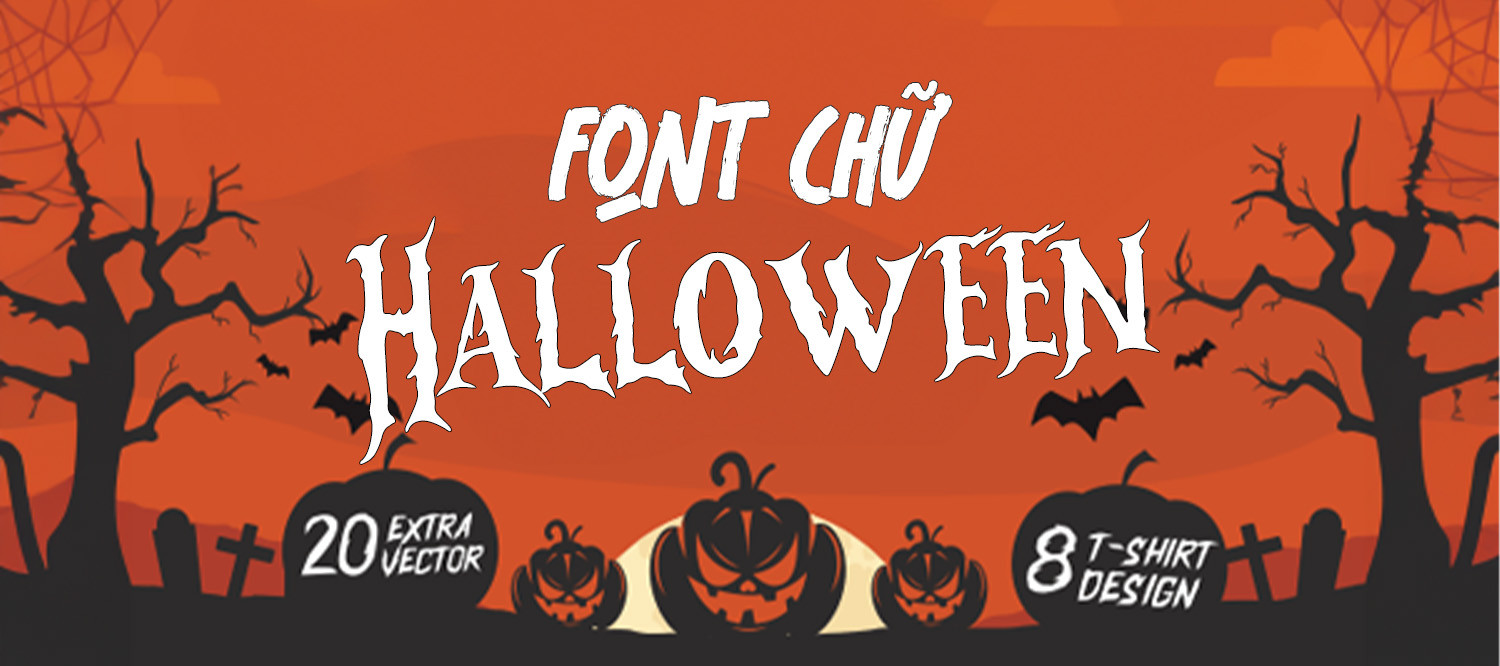
Halloween, ngày lễ kỳ bí và ma quái, luôn mang đến cho chúng ta cảm giác hồi hộp và thú vị. Để tạo ra những nội dung hấp dẫn và phù hợp với chủ đề này, việc sử dụng font chữ Halloween đóng vai trò vô cùng quan trọng. Những font chữ đặc biệt này không chỉ giúp thể hiện được không khí ma mị của Halloween mà còn là yếu tố quyết định trong việc thu hút sự chú ý và tăng cường tương tác của độc giả. Hãy cùng khám phá thêm về các loại font chữ Halloween và cách tận dụng chúng trong nội dung sáng tạo của bạn.
Font chữ Halloween là những loại font được thiết kế đặc biệt để phù hợp với chủ đề Halloween. Chúng thường có các đặc điểm nổi bật như hình ảnh ma quái, thiên về màu sắc tối và các yếu tố đồ họa đặc trưng như những con rắn, quái vật, hay chữ viết phát ra lửa. Việc sử dụng font chữ Halloween mang lại nhiều lợi ích đáng kể cho các chiến dịch truyền thông và nội dung liên quan đến Halloween.
Đầu tiên, chúng giúp tạo ra một không gian thú vị và kịch tính hơn cho người xem, từ đó thu hút sự chú ý một cách nhanh chóng.
Thứ hai, font chữ Halloween giúp tạo ra một phong cách nhất định cho thương hiệu hoặc sản phẩm của bạn trong mùa Halloween, từ đó gia tăng khả năng nhận diện thương hiệu.
Cuối cùng, những font chữ này thường đi kèm với tính tương tác cao, khiến cho người dùng dễ dàng chia sẻ và lan truyền thông điệp của bạn.
Dưới đây là top 8 font chữ Halloween được sử dụng phổ biến hiện nay. Mỗi loại font chữ này đều có tính chất và cảm giác riêng, phù hợp cho các dự án liên quan đến Halloween.
Font chữ brush SVN-Okami là một kiểu chữ chảy độc đáo, mang lại cảm giác thu hút và tự nhiên. Kiểu chữ này đặc biệt thích hợp cho những thiết kế trên nền màu nóng như đỏ và đen, tạo ra sự nổi bật và ấn tượng mạnh mẽ. Với đường nét uốn lượn và cảm giác phóng khoáng, SVN-Okami là sự lựa chọn hoàn hảo cho những thiết kế mang phong cách bí ẩn, ma quái, và kinh dị. Sự kết hợp giữa kiểu chữ chảy và nền màu nóng sẽ mang lại hiệu ứng thị giác mạnh mẽ, tạo nên một không gian đầy lôi cuốn và mê hoặc, thích hợp cho các sự kiện như Halloween hoặc những chủ đề liên quan đến thế giới huyền bí.
Font chữ Halloween brush SVN-Road Rage có sự kết hợp giữa nét vẽ sắc nét và hình ảnh đặc trưng của ngày Halloween. Được thiết kế với các đường nét uốn cong và in đậm, font chữ này tạo nên cảm giác huyền bí và ma mị. Màu sắc chủ đạo là màu trắng - đen, tôn lên sự đặc biệt và kỳ lạ của font chữ, mang lại một khung cảnh ma quái mà không cần sử dụng quá nhiều chi tiết ghê rợn.
Font chữ Brush TH Bloody Camp Trial là một lựa chọn hoàn hảo cho các thiết kế Halloween với phiên bản Việt hóa độc đáo. Được thiết kế theo kiểu chữ chảy như máu, font chữ này tạo ra một hiệu ứng đặc biệt, mang đến cảm giác rùng rợn và đầy bí ẩn. Với các tông màu nóng như đỏ và cam làm chủ đạo, TH Bloody Camp Trial thực sự nổi bật và thu hút sự chú ý. Sự kết hợp giữa các yếu tố này tạo nên một không gian huyền bí rất thích hợp cho các thiết kế mang chủ đề bí ẩn, ma quái hay kinh dị. Font chữ này không chỉ làm tăng tính thẩm mỹ mà còn góp phần tạo nên một không khí đáng sợ và hồi hộp cho bất kỳ dự án nào.
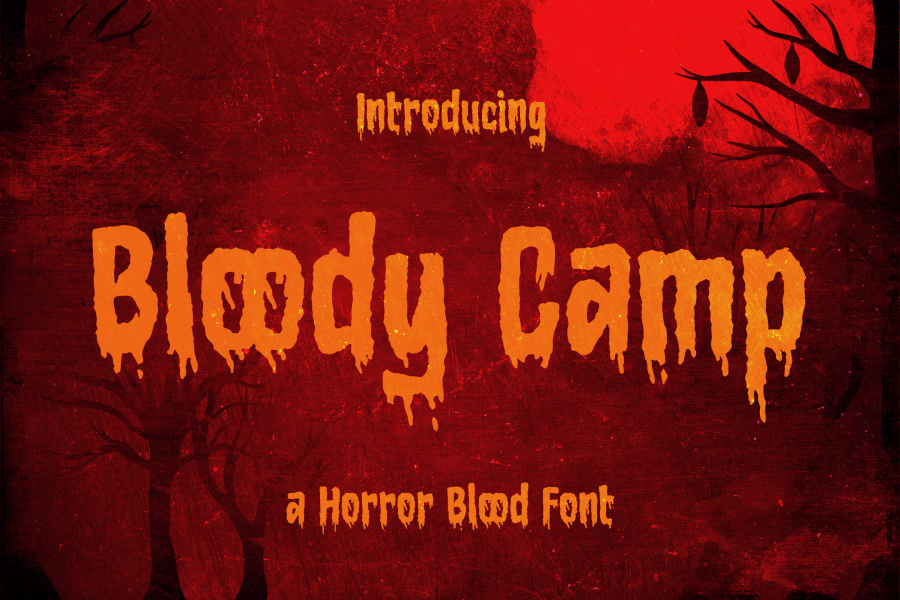
TH Death World là một font chữ Halloween Việt hoá với nét chữ nguệch ngoạc và kiểu dáng chữ kỳ dị, tạo nên một phong cách độc đáo và nổi bật. Màu sắc chủ đạo của font chữ này là tông màu đen-đỏ, mang lại sự tương phản mạnh mẽ và tạo ra cảm giác huyền bí, ma mị. Điều này làm cho TH Death World trở thành sự lựa chọn hoàn hảo cho các sản phẩm thiết kế liên quan đến Halloween, truyện tranh kinh dị, phim hoặc các dự án mang phong cách ma quái. Font chữ này không chỉ thu hút người nhìn mà còn gợi lên cảm giác rùng rợn, đầy ám ảnh, rất phù hợp để tạo nên không gian và cảm xúc đặc trưng cho các dự án sáng tạo.
Font chữ TH Battlesbridge là một font chữ cổ điển, mang phong cách vintage với nét đặc trưng là những đường cong đậm và sắc nét. Kiểu chữ này gợi nhớ đến những thập niên trước, tạo nên cảm giác hoài cổ và đầy bí ẩn. Với những đường nét mềm mại nhưng mạnh mẽ, TH Battlesbridge rất phù hợp để sử dụng trong các dự án có chủ đề Halloween hoặc thể loại rùng rợn. Nó không chỉ giúp làm nổi bật tiêu đề mà còn mang lại không khí ma quái, kỳ bí, làm tăng thêm phần hấp dẫn và cuốn hút cho nội dung. Sử dụng TH Battlesbridge, bạn sẽ dễ dàng tạo ra những thiết kế đầy ấn tượng và độc đáo, đặc biệt là trong các sự kiện và dự án nghệ thuật cần sự phá cách và sáng tạo.
Font chữ TH Mironta là sự kết hợp hài hòa giữa sự cổ điển và đương đại, mang đến một phong cách độc đáo và cuốn hút. Với thiết kế vui vẻ, dễ thương và đầy cute, TH Mironta dễ dàng thu hút ánh nhìn và tạo cảm giác thân thiện, ấm áp cho người xem. Font chữ này rất thích hợp cho nhiều loại dự án khác nhau, từ thiết kế đồ họa cho các ấn phẩm in ấn, quảng cáo, logo, đến các dự án trực tuyến như website và ứng dụng di động. Với TH Mironta, bạn có thể mang lại một diện mạo mới mẻ và sinh động cho bất kỳ sản phẩm nào, giúp truyền tải thông điệp một cách hiệu quả và ấn tượng.
Font chữ Danger Night là một sự kết hợp tuyệt vời giữa hiện đại và bí ẩn. Với kiểu chữ góc cạnh sắc nét, nó mang lại cảm giác mạnh mẽ và cứng cáp. Sự đối lập mạnh mẽ giữa tông màu đen và trắng tạo ra một hiệu ứng thị giác ấn tượng, làm nổi bật bất kỳ thiết kế nào mà nó xuất hiện. Font chữ này đặc biệt thích hợp cho các dự án thiết kế liên quan đến Halloween, kinh dị, hiphop, và các tác phẩm nghệ thuật sáng tạo khác. Với sự pha trộn giữa tính hiện đại và sự huyền bí, Danger Night chắc chắn sẽ làm cho bất kỳ thiết kế nào trở nên nổi bật và cuốn hút.
Broken Dreams là một font chữ cổ điển mang phong cách vintage, đầy nghệ thuật và sáng tạo. Với đường nét tròn tinh tế và sự kết giữa các yếu tố cổ điển và hiện đại, Broken Dreams tạo ra một kiểu chữ độc đáo, thích hợp cho việc thiết kế những bản thiết kế nổi bật, poster nghệ thuật và các tiêu đề đặc biệt. Sự mạnh mẽ trong từng nét chữ của Broken Dreams giúp truyền tải thông điệp một cách rõ ràng và ấn tượng, làm nổi bật bất kỳ dự án thiết kế nào mà nó được sử dụng.
Trên đây là những thông tin cơ bản về font chữ Halloween và cách áp dụng chúng vào nội dung sáng tạo của bạn. Việc lựa chọn và sử dụng đúng font chữ không chỉ giúp nâng cao hiệu quả truyền thông mà còn là yếu tố quan trọng trong việc xây dựng thương hiệu và thu hút sự quan tâm từ phía khán giả.